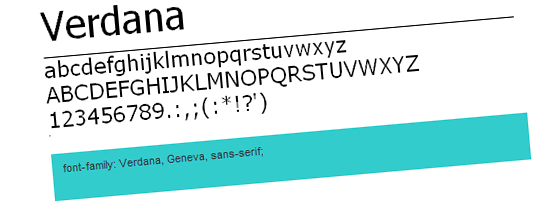
21 tipografías Web seguras
Los tipos de letras son uno de los bloques más importantes en la construcción del diseño Web. Un problema habitual en los tipos de letras tradicionales (Verdana, Arial, Helvetica, etc.), es que tarde o temprano te hartas de ellas. Aunque no hay nada de malo en ellas, ya que son tres de las tipografías más seguras.
Por otra parte, si utilizas un tipo de letra poco frecuente que los usuarios no tienen en su sistema, a demás de ser una opción poco profesional, al no tener control sobre lo que el usuario verá en su navegador. Por eso los diseñadores prefieren la tipografía que se ha dado en llamar segura. ¿Cuán seguras son las tipografías Web? Ese tipo de letras se ven bien en pantalla y son relativamente populares, por lo que puede asumir con seguridad que tus visitantes tendrán esa tipografía en su sistema.
Por regla general esos tipos de letras vienen con el sistema operativo, y que los usuarios las tienen instaladas por defecto. Otros tipos de letras, no hay garantía de que las pueda tener instaladas en el ordenador del usuario. Incluso si esa tipografía está instalada en los ordenadores de los usuarios, muchas de ellas solo se ven bien en ciertos casos, como puede ser con ciertos tamaños, en donde aparecen distorsionadas o son ilegibles. Después de todas estas aclaraciones, necesarias para tener claro los conceptos, y saber por tanto que decisión tomar, debe tomar.